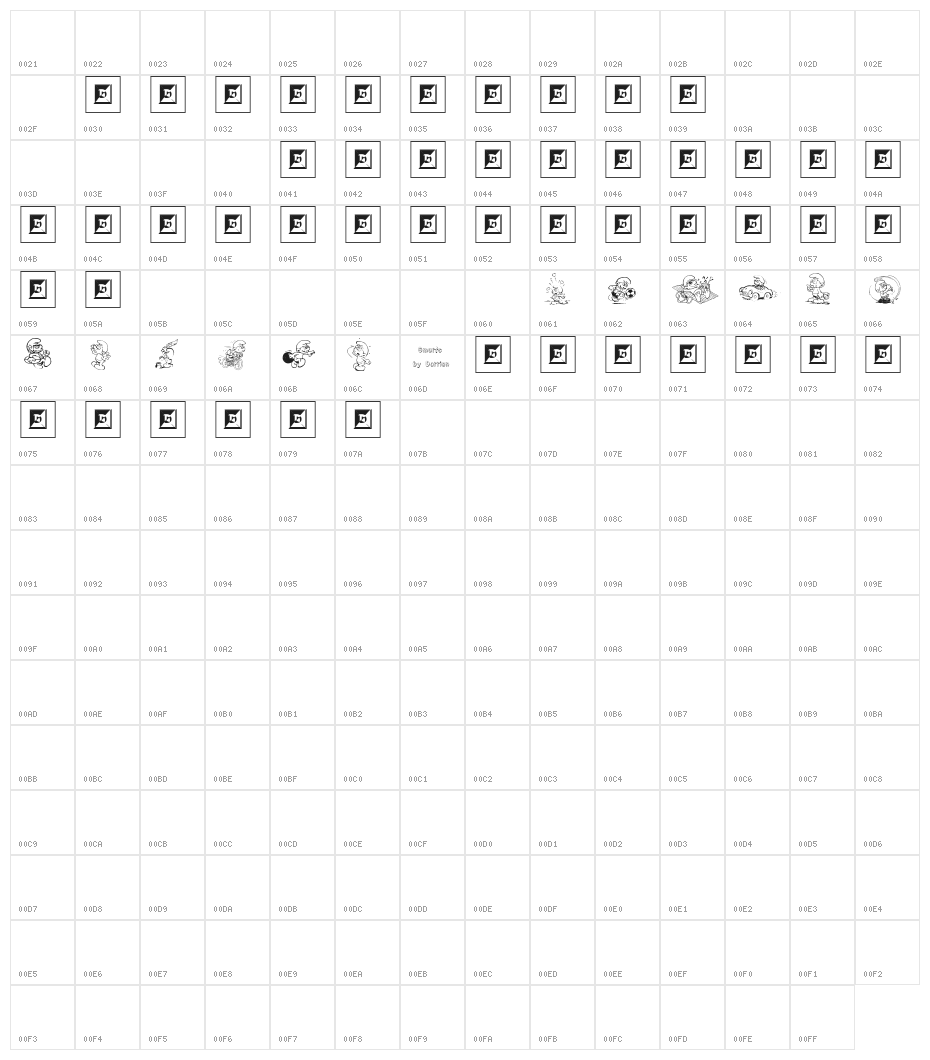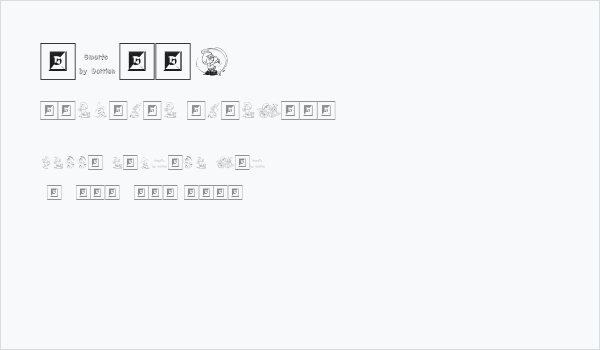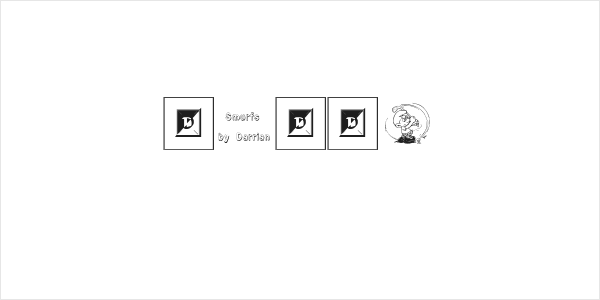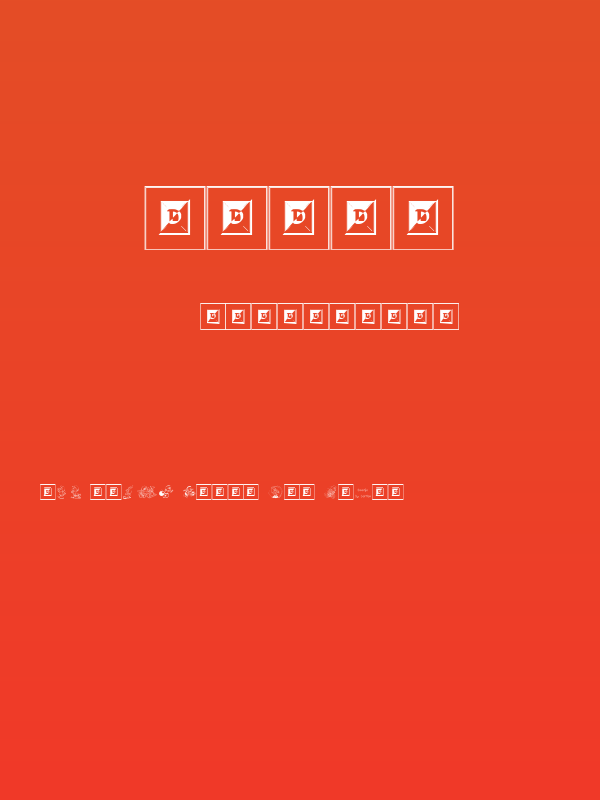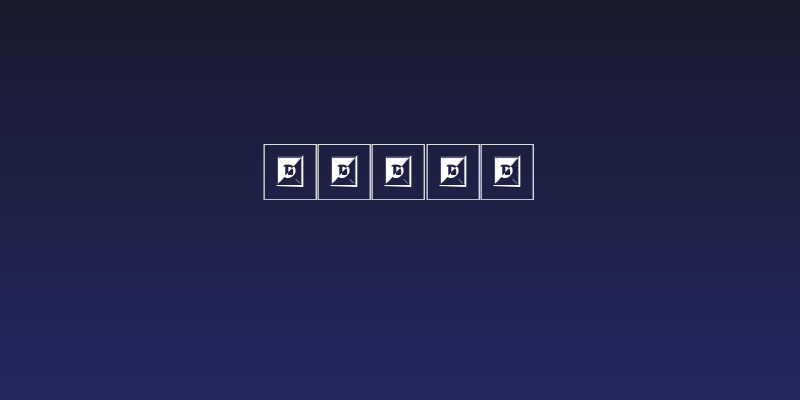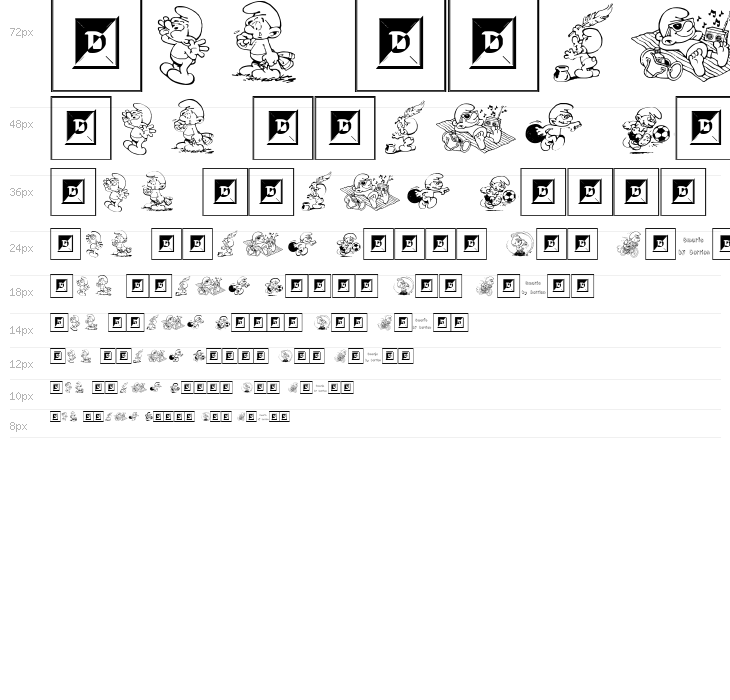
Smurf Font
| Estilo general | Decorative, Playful, Cartoonish |
| Caso de uso | Logos, Posters, Themed Headlines, Children's Materials |
| Proyectos propuestos | Children's books, themed party invitations, comic strips, playful branding, novelty posters. |